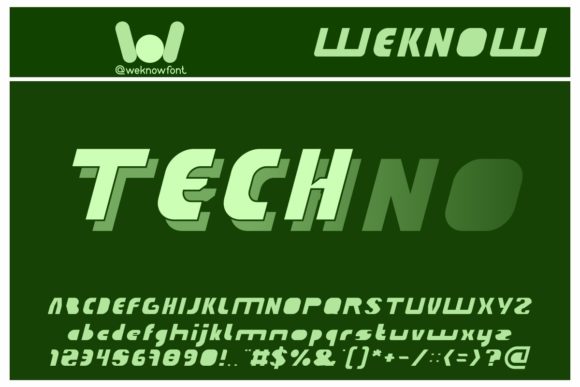
Techno Tech
Trovare i giusti elementi di design può essere difficile, ma Techno Tech offre una collezione eccezionale che eleva istantaneamente il tuo lavoro.